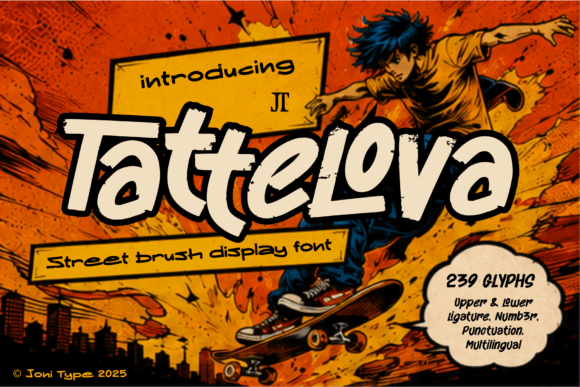
Tattelova
Jika anda sedang mencari aset berkualiti tinggi seperti Tattelova, pakej premium ini merupakan pilihan yang hebat untuk projek kreatif anda.
Sama ada anda mencipta produk POD (Print on Demand), jemputan perkahwinan atau grafik media sosial, Tattelova amat bersesuaian.